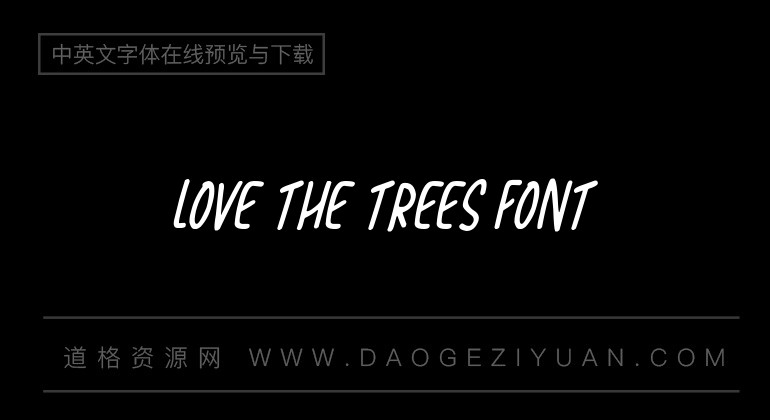
Love The Trees Font
Love The Trees Font 是一款自然、风格清新的手写字体,适合用于描绘自然、植物和环保等主题。这个字体的特点是有一些连笔,让字母看起来更加流畅和自然,同时也有一些细节上的装饰,增强了字体的可爱感和个性化。这款字体支持英文字母、数字和一些常见标点符号。它可以被用于海报设计、明信片、广告和其他创意设计项目。
Love The Trees Font是一款非常不错的手写艺术字体,具有很好的视觉感,适合于文化类的宣传设计、商业类品牌的广告和产品包装设计以及个性化文字排版等较多场景。